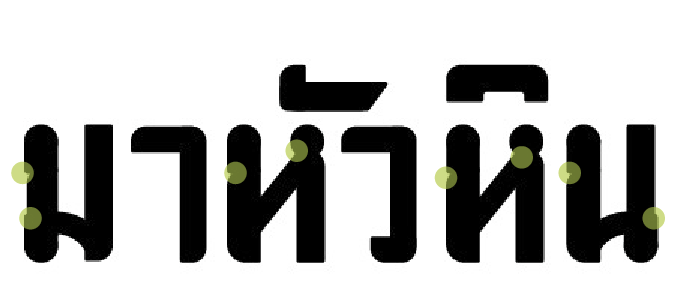
มาอยู่หัวหินได้ปีกว่าๆ เห็นแล้วเลย
ผมมาทำงานอยู่หัวหินได้ปีกว่าๆ แล้วเห็นไอ้ป้าย "หัวหิน" แล้วเกิดความสงสัยว่า f0nt อะไร เห็นเต็มไปหมด
แล้วพอต้องทำสื่อในหัวหิน เลยคิดว่าจะทำ f0nt ไอ้แบบนี้จะดีไหม
แบบอักษรเก่าๆ แบบนี้มีลิขสิทธิ์หรือปล่าวครับ ถ้ามีจะได้ทำไว้ใช้เอง(ไม่ต้องเสียตัง) ถ้าไม่มีจะได้ทำไว้แจก(ทำเอามันส์)
แบบอักษรแบบนี้ไม่มีลิขสิทธิ์ครับ
ถ้าอยากทำก็สามารถทำได้เลย
แล้วก็มีนักออกแบบตัวอักษรที่ชื่นชอบการอนุรักษ์แบบตัวพิมพ์ที่ทำแบบนี้เหมือนกันด้วยจ้ะ
ลองๆ ทำดูแล้วจะเอามาให้ด่าเรื่อยๆนะครับ
ไม่รู้จะวางแผนยังไงเลย ลองลุยๆทำๆไปเลย
ตรงบริเวณส่วนที่คว้านเข้าไปถ้าย่อฟอนต์ขนาดเล็กลงน่าจะหายไปนะครับ
อาจจะลองคว้านให้มากกว่านี้ดูครับ  :40: